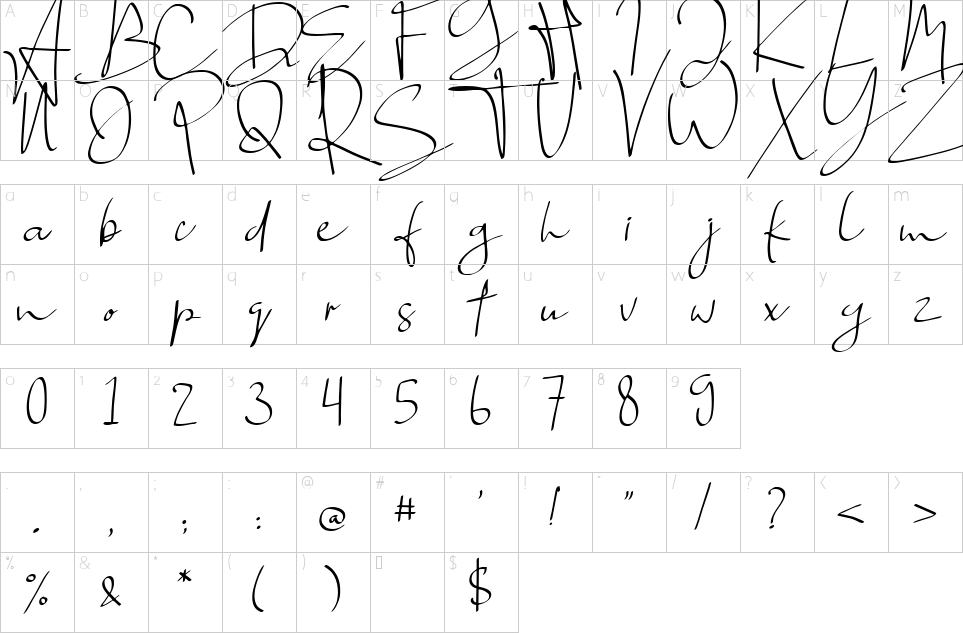
A fonte Mongoill é um recurso grátis que oferece uma estética atraente e versátil para qualquer projeto gráfico. Desenvolvida pela DYSA Studio, essa fonte vem em versões para Windows e Mac, permitindo que qualquer pessoa utilize seus recursos sem precisar de uma assinatura premium. Com 1,293 usuários que já a baixaram, é claro que essa fonte está ganhando popularidade entre designers e criadores de conteúdo. Se você está procurando por uma fonte elegante e moderna, não há melhor lugar para começar do que a Mongoill. Ela oferece o equilíbrio perfeito entre legibilidade e estilo, tornando-se uma excelente escolha para qualquer projeto. Download a Mongoill e descubra por si mesmo por que ela está ganhando tanta popularidade.